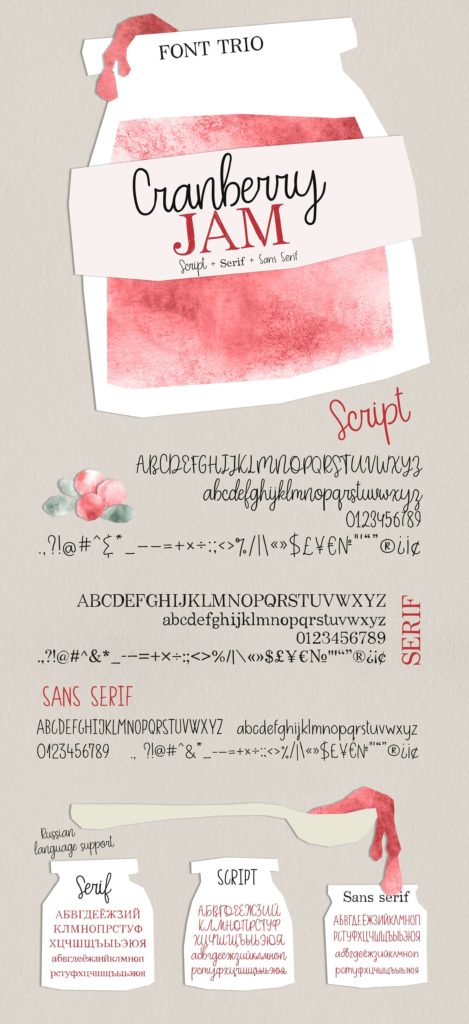
Это уникальный набор из трех гарнитур (Script, Serif и Sans Serif), разработанный независимым дизайнером Anmark. Это не просто один шрифт, а целая типографическая система в стиле рукописного акцидентного письма. Шрифт отличается естественностью линий, имитирующих написание пером или маркером с легким наклоном и неровностями краев, что придает тексту «живой» характер. Набор включает кириллическую раскладку, адаптированную под стилистику оригинала, что делает его доступным для русскоязычных дизайнеров. Благодаря своему выразительному рисунку букв, он отлично подходит для создания запоминающихся заголовков, логотипов и оформления упаковки. Скачать бесплатно кириллический вариант можно на нашем сайте